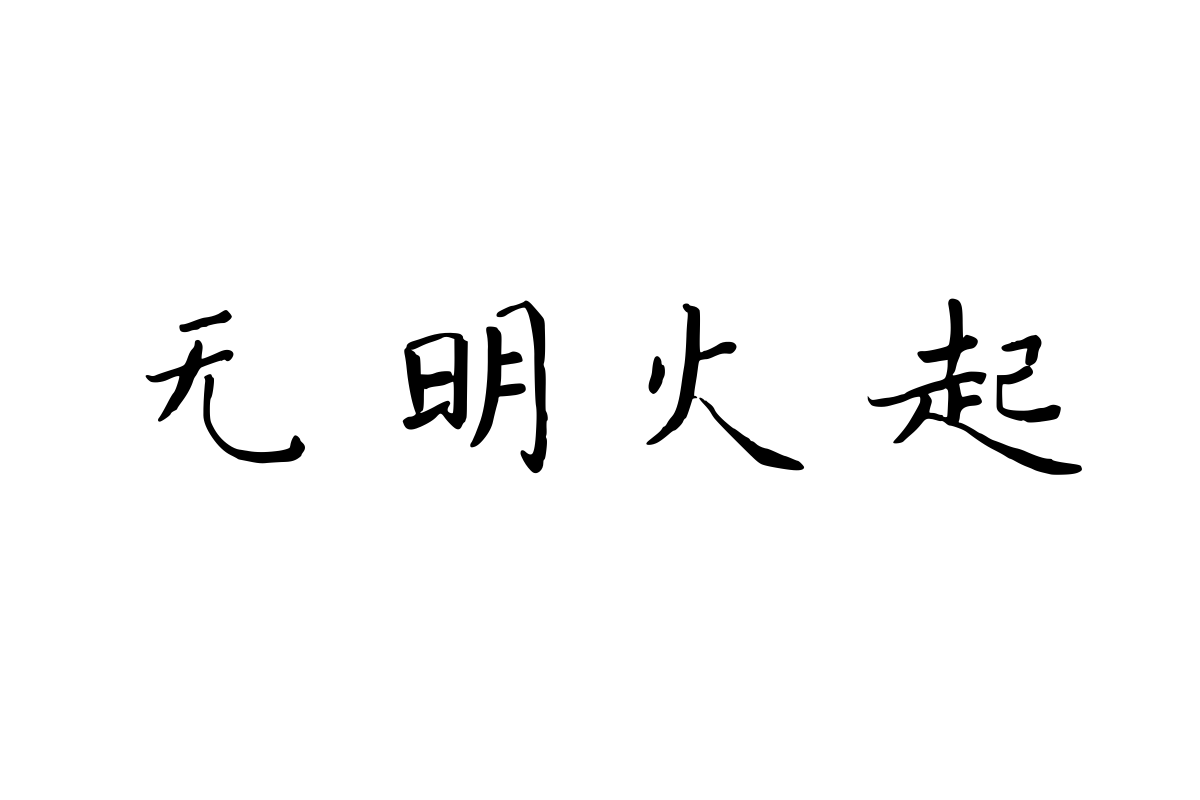
兰米硬笔楷体是一种硬笔书法字体,它以简洁、清晰、易读为特点。这种字体的特点是笔画粗细均匀,线条流畅,结构紧凑,给人一种整齐划一的感觉。兰米硬笔楷体的笔画粗细适中,既有力度又不失柔美,非常适合用于书写汉字和英文字母。它的设计灵感来源于中国传统的楷书,但又融入了现代审美的元素,使得它在保持传统韵味的同时,也具有很高的艺术价值和实用性。